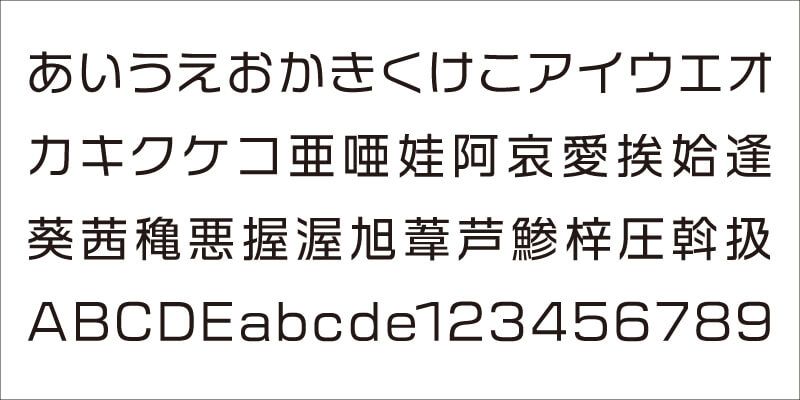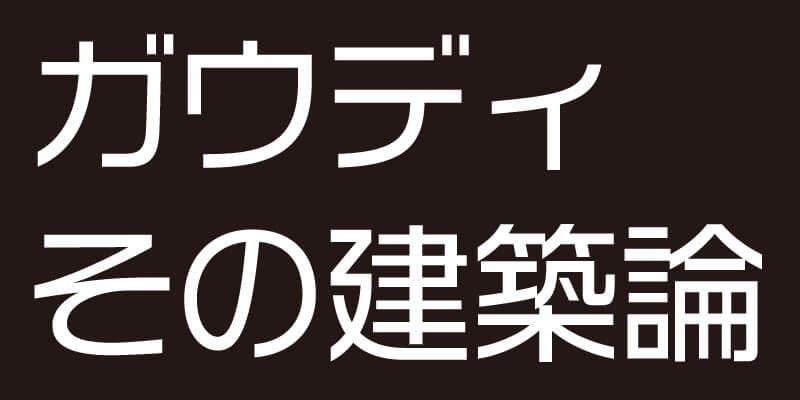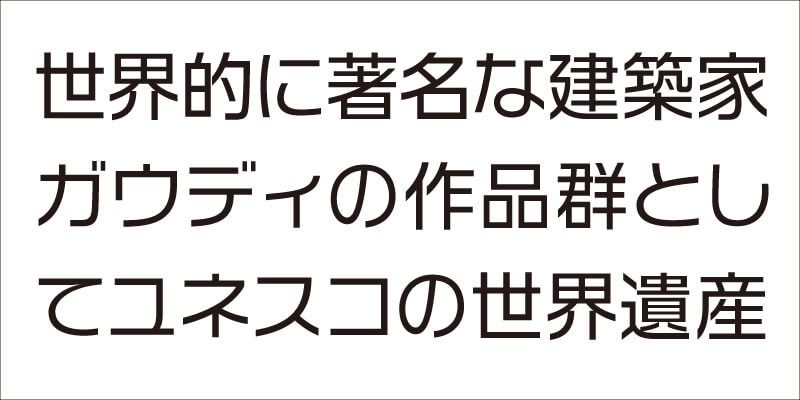
VDL-Logona는 서체에 요구되는 수준의 가독성과 더불어 전통적인 미학을 더욱 확장하고 발전시켜 정통 고딕(산세리프) 서체로 탄생했습니다. 현대 디지털 미디어 환경에서 그래픽 표현에 적합합니다. 가시성, 가독성, 판독성이 크게 향상되어 이 서체로 설정된 텍스트는 높은 수준의 안정성과 균일성을 가지고 있습니다. 단정하고 깔끔한 모습이 매력입니다.